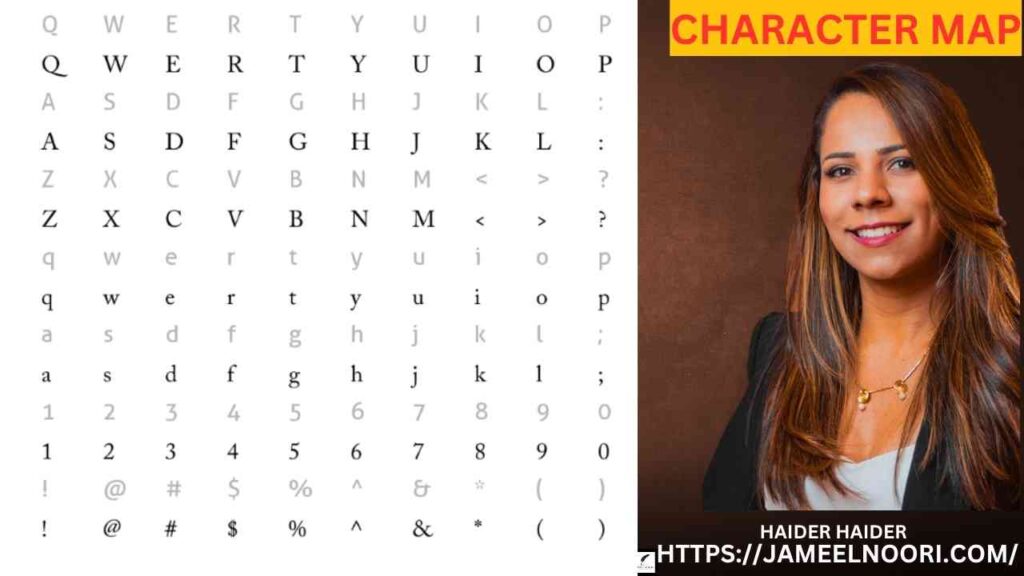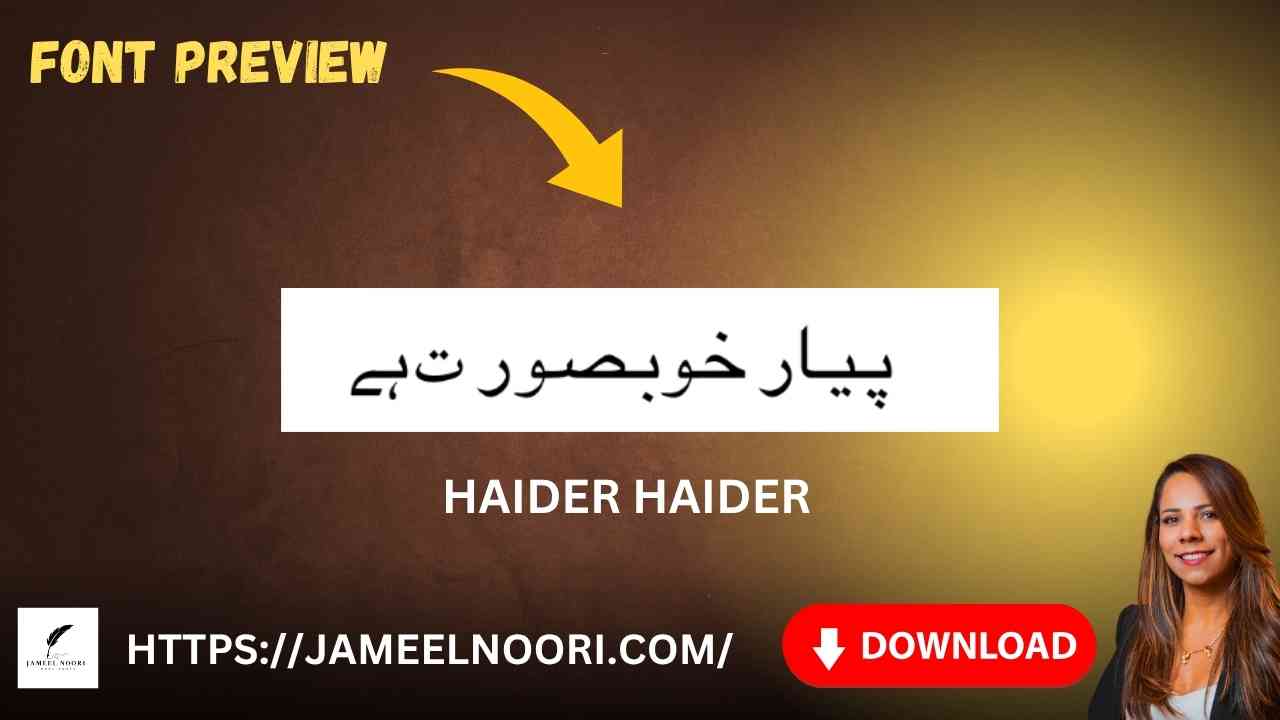
Download Urdu font Haider – Kya Ye Font Aapke Liye Behtareen Hai?
Agar aap Urdu likhne aur design banane ka shauq rakhte hain, to Download Urdu font Haider aapke liye ek zabardast choice ho sakta hai. Ye font stylish aur readable hai, jo log Urdu novels, headings, ya posters ke liye unique look chahte hain unke liye perfect hai. Is font ko ab tak 7654 martaba download kiya ja chuka hai, jo iski popularity ka proof hai.
Download Urdu Font Haider – Key Features You Must Know
Download Urdu font Haider font ke kuch khas features usay market me dusre Urdu fonts se alag banate hain:
- Stylish aur clean design
- Perfect for digital aur print design
Yeh font Haider family style me design kiya gaya hai jiska har character artistic touch rakhta hai.
Aap is font ko Lahore, Karachi, aur Pakistan ke kisi bhi sheher me Urdu designers ke darmiyan mashhoor paayenge.
Download Urdu font Haider – Best Use Cases for Urdu Designers
Download Urdu font Haider ka use kai purposes ke liye kiya ja sakta hai:
- ✔️ Urdu poetry posters
- ✔️ Novel titles
- ✔️ Calligraphy artwork
- ✔️ Social media Urdu quotes
- ✔️ Presentation headings
Agar aap freelance Urdu designer hain, to yeh font aapke design portfolio ko aur bhi behtareen bana sakta hai.
What is Haider font used for?
Haider font is used for stylish Urdu writing, especially for poetry, headings, and graphic design.